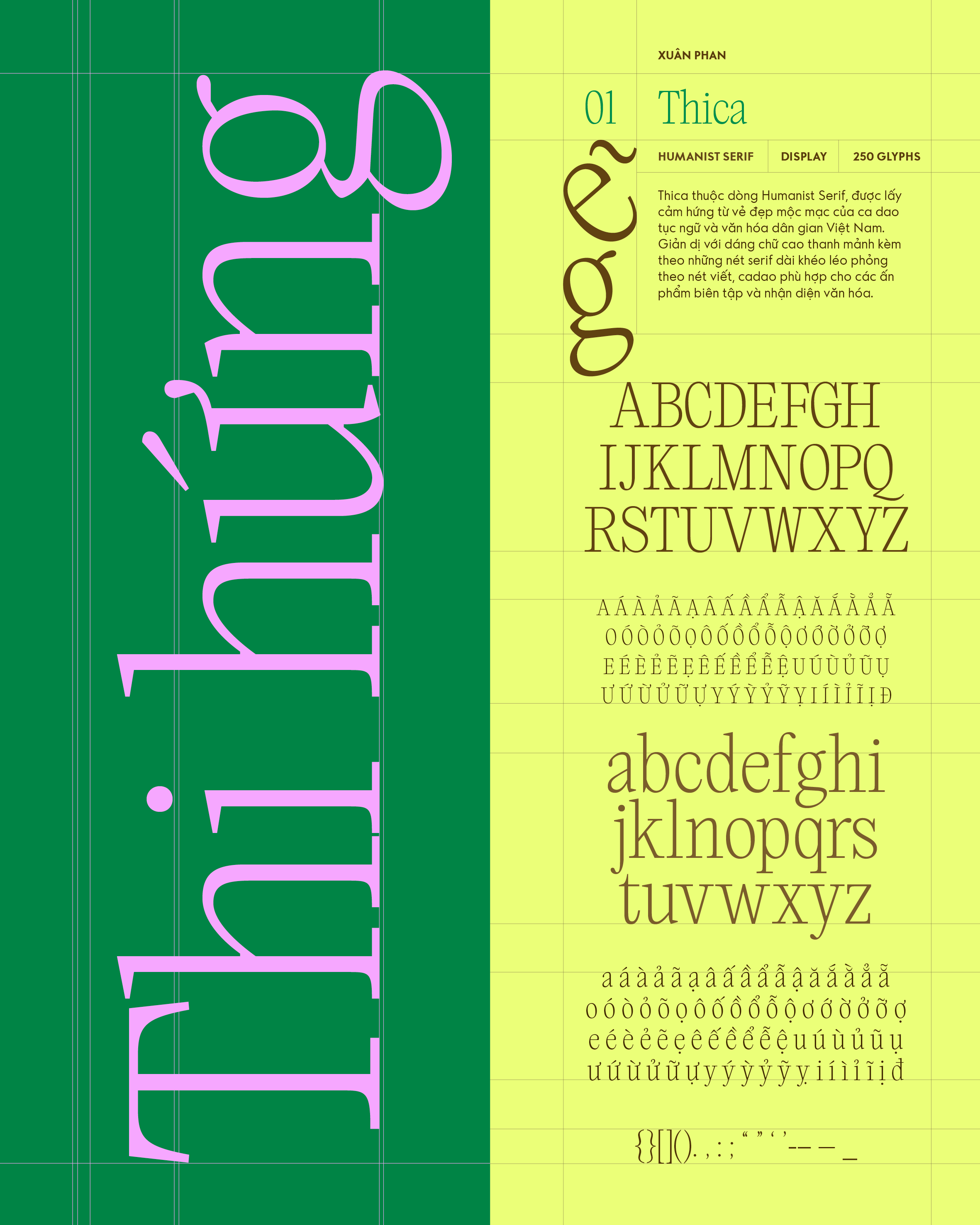
Thica
Về Thica: Thica thuộc dòng Humanist Serif, được lấy cảm hứng từ vẻ đẹp mộc mạc của ca dao tục ngữ và văn hóa dân gian Việt Nam. Giản dị với dáng chữ cao thanh mảnh kèm theo những nét serif dài khéo léo phỏng theo nét viết, cadao phù hợp cho các ấn phẩm biên tập và nhận diện văn hóa.
Humanist Serif
Display
Xuân Phan